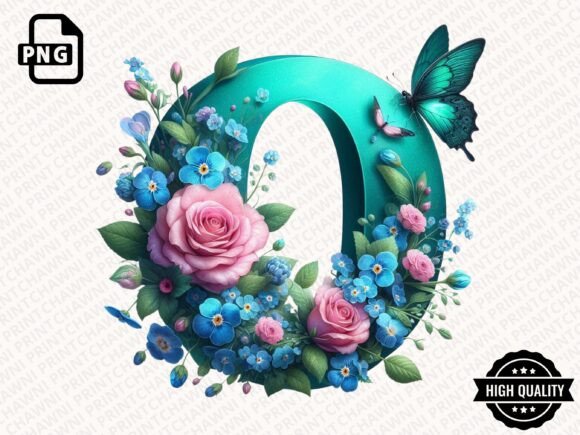
Roses & Butterflies Alphabet Clipart PNG
Việc tìm kiếm các thành phần thiết kế phù hợp có thể là một thách thức, nhưng Roses & Butterflies Alphabet Clipart PNG cung cấp một bộ sưu tập đặc biệt giúp nâng tầm công việc của bạn ngay lập tức.
Được chế tác với độ chính xác cao, Roses & Butterflies Alphabet Clipart PNG cung cấp các vector sạch, kiểu chữ mượt mà và giấy phép thương mại để bạn yên tâm.